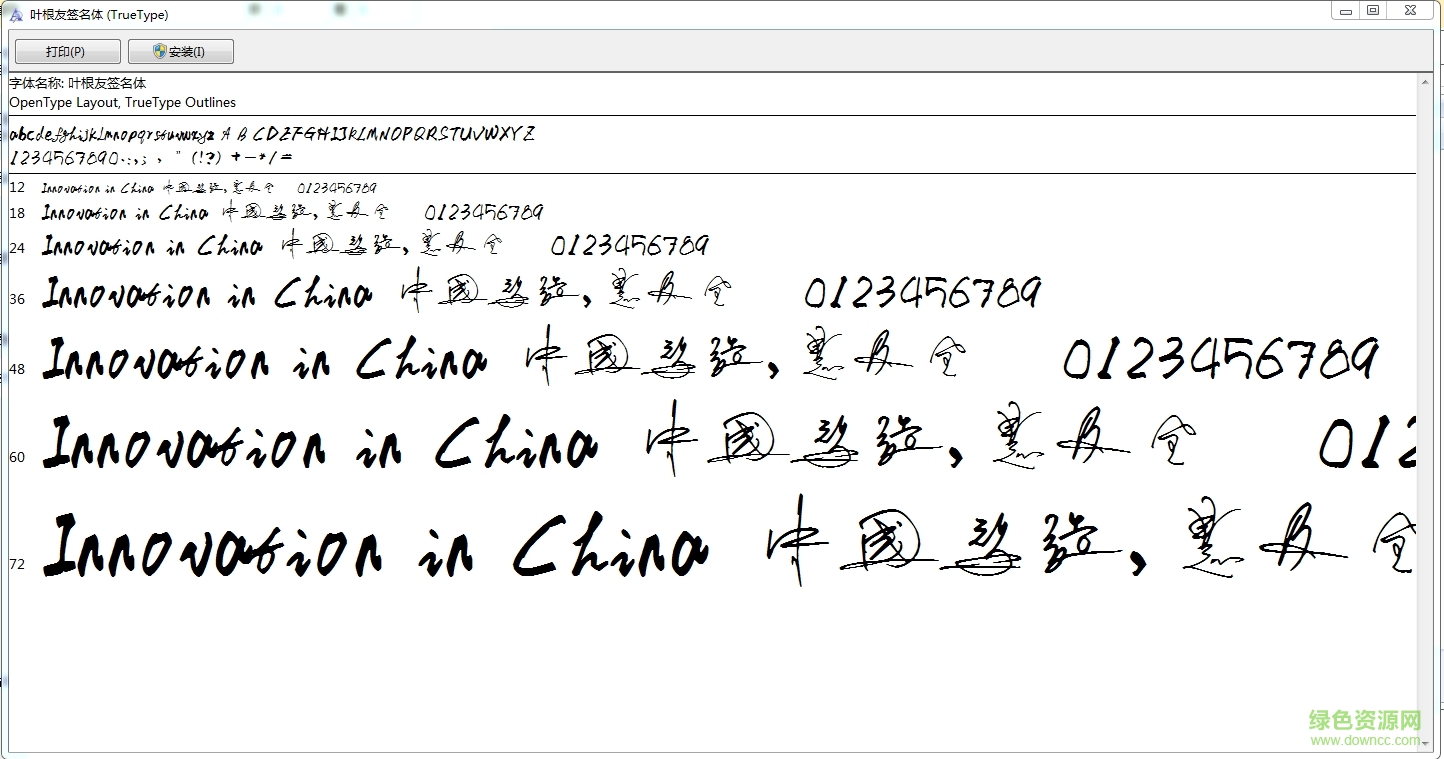
葉根友簽名體是葉根友先生多年設(shè)計(jì)經(jīng)驗(yàn)的結(jié)晶,適用于簽名藝術(shù)、書法、信函等。共有中國(guó)姓氏(復(fù)姓)1008個(gè),姓名相關(guān)漢字1775字。無(wú)論是準(zhǔn)備制作PS,平面設(shè)計(jì),還是印章,以及噴繪都是很好的選擇。喜歡的小伙伴快來(lái)綠色資源網(wǎng)下載吧!